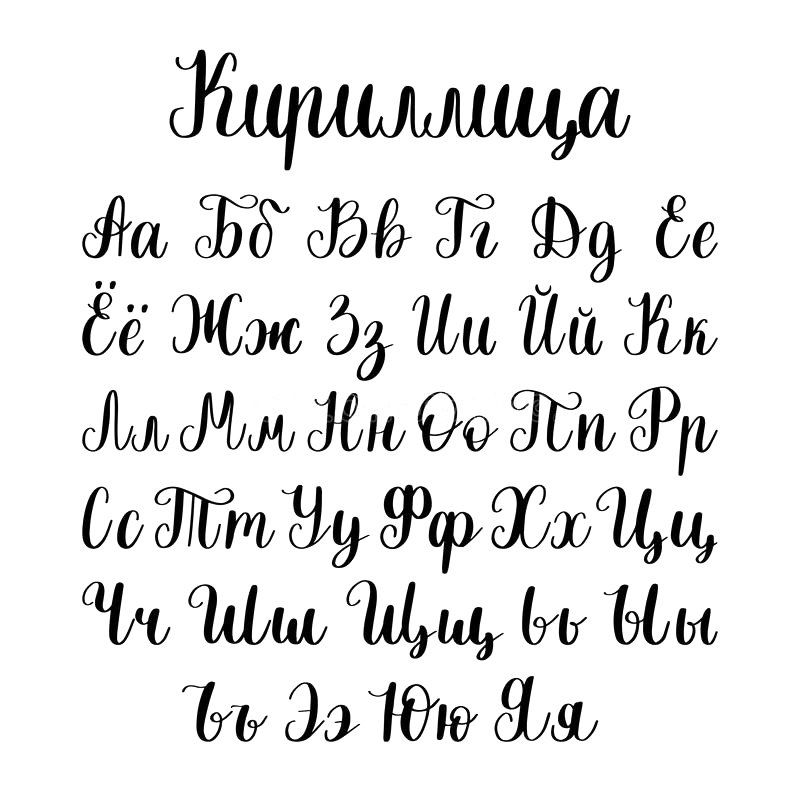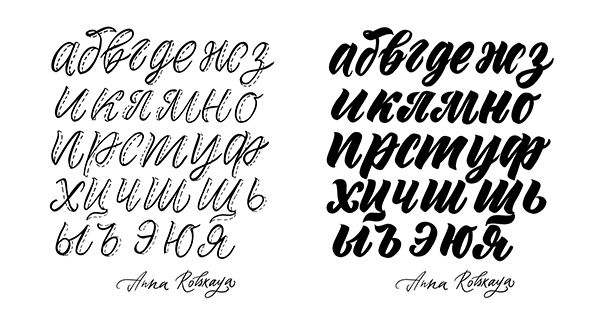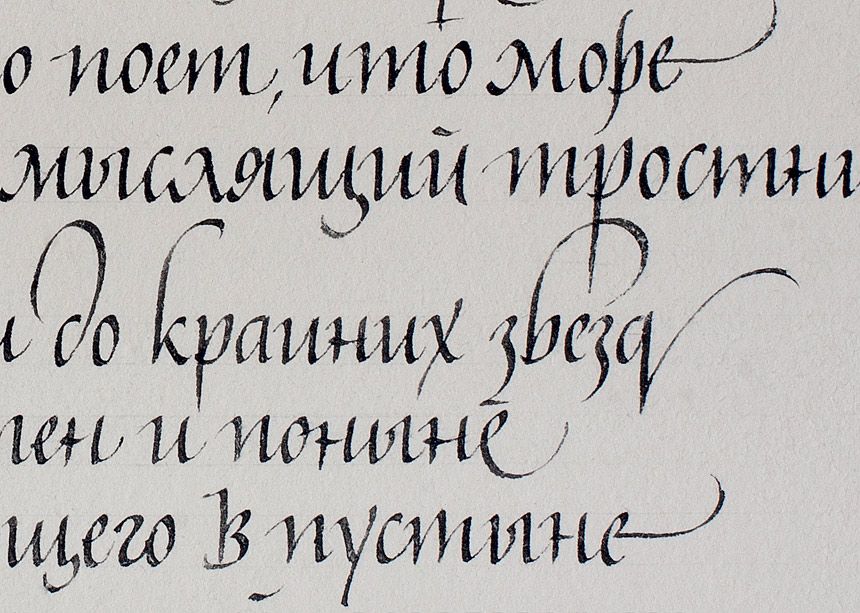
Прописной шрифт русский жирный: Рукописные шрифты — русские скачать бесплатно
Навык менять стиль текста пригодится не только чтобы навести красоту и сделать сообщение более читаемым, выделив важное жирным курсивом и т.д. С помощью нужного начертания текста, можно также упростить читателю жизнь при копировании нужной информации.
Так текст, написанный моноширинным шрифтом, можно скопировать при одном нажатии. Пометочка: функция доступна только на мобильных устройствах и планшетах.
Выделяйте моноширинным текстом номера телефонов, email-адреса, банковские реквизиты, промокоды и т.д.
На этом порция обучалок по мэджик-скилз на сегодня закончена. Надеемся было полезно и Ваши отношения с Telegram станут более теплыми. А у нас тут тепло всегда, поэтому заходите на огонек.
Журнал «Шрифт» • 10 шрифтов Владимира Ефимова
6 мая исполнилось 70 лет со дня рождения шрифтового дизайнера Владимира Ефимова (*6 мая 1949 †23 февраля 2012). Мы выбрали 10 шрифтов Владимира Венедиктовича и сопроводили их комментариями, которые он записал в 2010 году для выставки «Шрифтовых дел мастер» в Музее архитектуры. Позже они были помещены в небольшом каталоге, выпущенном компанией ParaType.
Мы публикуем комментарии с небольшими сокращениями. Список начинается со шрифтов, которые не всегда связывались в сознании читателей с «академическим» стилем Владимира Ефимова. Между тем его кириллизации шрифтов Джонатана Барнбрука, студии «Эмигре» и других прогрессивных в 90-е годы словолитен и сегодня остаются мастерскими и смелыми проектами, о которых мы считаем нужным напомнить.
☛ ITC Avant Garde Gothic
Владимир Ефимов: «Авангард Готик — главный шрифт ITC, которым они безумно гордились. До того, как мы начали официальную работу над этим шрифтом, Максим Жуков уже заставлял меня рисовать eгo варианты для разных языков. Издательство „Мир“ выпускало литературу на русском и иностранных языках. Часть этих языков была восточная. Были издания для Индии, Афганистана и других стран.